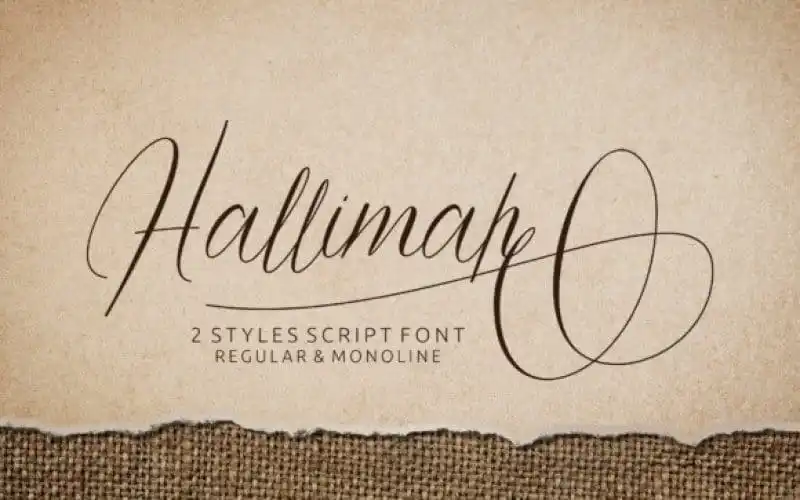
Hallimah Script Font – Fonte Grátis
Hallimah Script Font
Hallimah Script é uma fonte escrita a mão que cativa por completo quem a experimentar. Inspirada nos estilos clássicos de tipografia, Hallimah oferece seu próprio estilo único para qualquer projeto de design. Seu designer, Hamilton, trouxe à vida essa fonte com um toque cuidadoso e meticuloso, criando algo verdadeiramente especial. Seja você designer ou artista gráfico, esta é uma parceria perfeita entre os dois mundos do texto e da arte. Suas curvas fluidas são como um encorajamento constante em seu trabalho de design, enquanto sua elegância única enriquece qualquer projeto com o qual ela é utilizada. Hallimah Script não é apenas para headlines ou t-shirts; também é perfeita para logotipos, frases escritas a mão e até mesmo inscrições em cartões de felicitações. Está pronto para mergulhar nesse charme? Comece seu próximo projeto com Hallimah Script. Seja ele um design editorial complexo ou uma frase simplesmente bonita no centro do seu trabalho, Hamilton’s Hallimah Script é certamente o elemento que tornará sua obra ainda mais única e atraente.